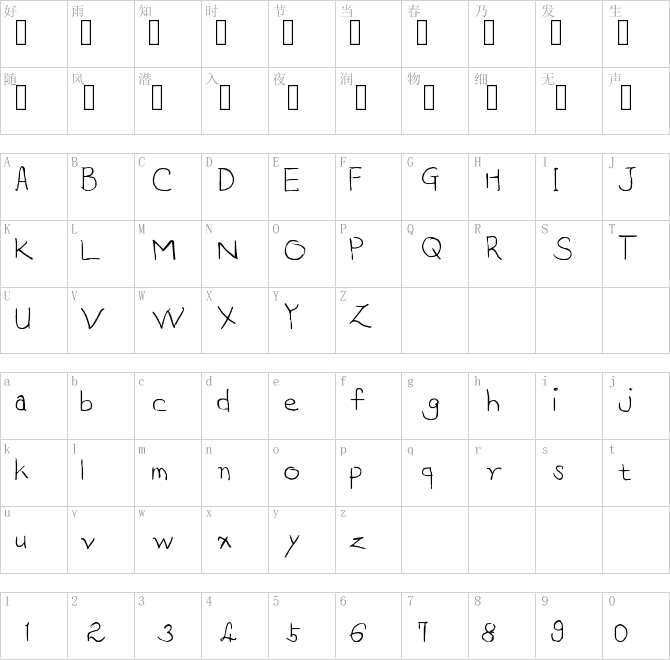
나눔손글씨 바른정신韩国字体
나눔손글씨 바른정신韩国字体,这款字体结构工整、笔画清晰,兼顾美观与易读性,适用于标题、正文、海报、包装、LOGO 等多种场景。字形优雅稳定,风格百搭耐看,适配日常排版与创意设计,让文字呈现更舒适、更具质感。나눔손글씨 바른정신韩国字体一笔一画,皆是细节,以均衡的比例、流畅的线条打造舒适视觉体验,字形端正大气,风格简约现代。无论是商业设计、品牌宣传还是日常排版,都能轻松驾驭,让文字更有格调与力量。나눔손글씨 바른정신韩国字体字体下载。